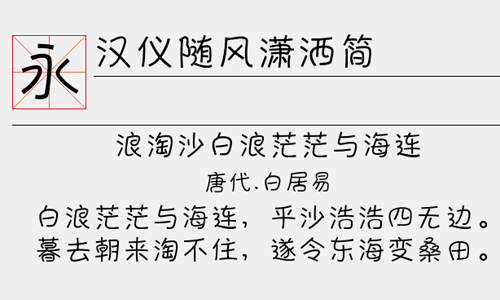
漢儀隨風(fēng)瀟灑簡(jiǎn)字體是由漢儀字庫(kù)出品的中文字體,此款字體線條灑脫奔放,結(jié)構(gòu)簡(jiǎn)省,筆形富于變化,靈動(dòng)優(yōu)雅,極富意趣,可以用于海報(bào)設(shè)計(jì)、古風(fēng)設(shè)計(jì)或是裝飾用字。歡迎喜歡漢儀隨風(fēng)瀟灑字體的朋友前來(lái)下載使用。